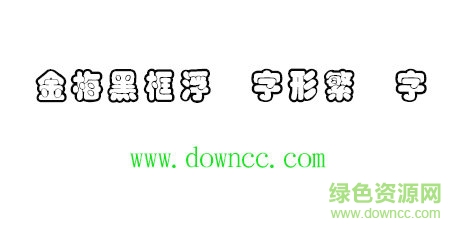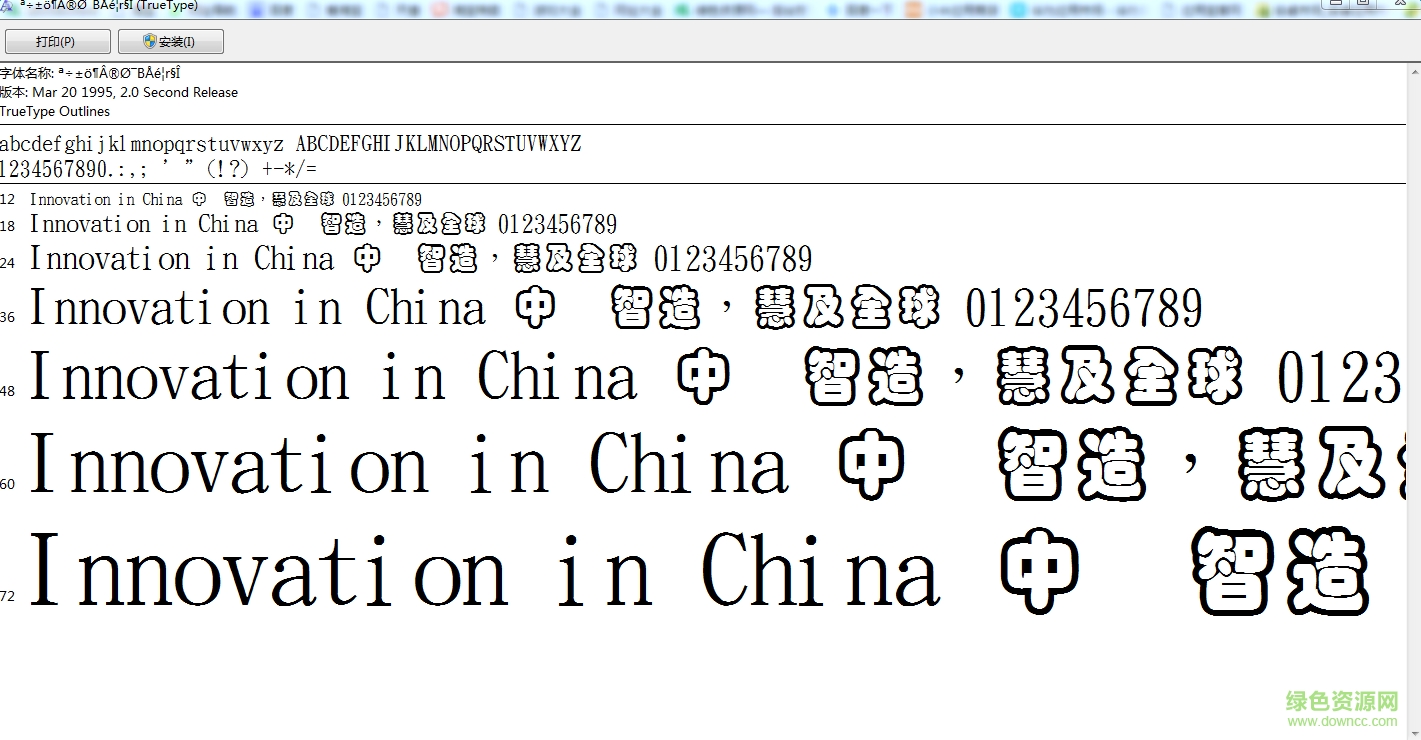
金梅黑框浮體字形是一款空心的金梅字體,字形工整,筆墨飛動(dòng),自帶黑框效果,印刷出來(lái)非常美觀,適合經(jīng)常出版特殊新聞信息的朋友們使用,雖然字體一般很少見(jiàn),但是還挺實(shí)用的,有需要者歡迎在綠色資源網(wǎng)下載!
金梅黑框浮體字形是款用于美工設(shè)計(jì)方面的字體,該字體圓轉(zhuǎn)飛動(dòng),欹正相參,風(fēng)度超逸,看上去十分美觀,整體效果非常統(tǒng)一,且字庫(kù)完整,可以廣泛應(yīng)用于出版印刷、美術(shù)設(shè)計(jì)、宣傳海報(bào)、ppt、影視制作以及內(nèi)容用字等領(lǐng)域,有需要的朋友可以免費(fèi)下載收藏。